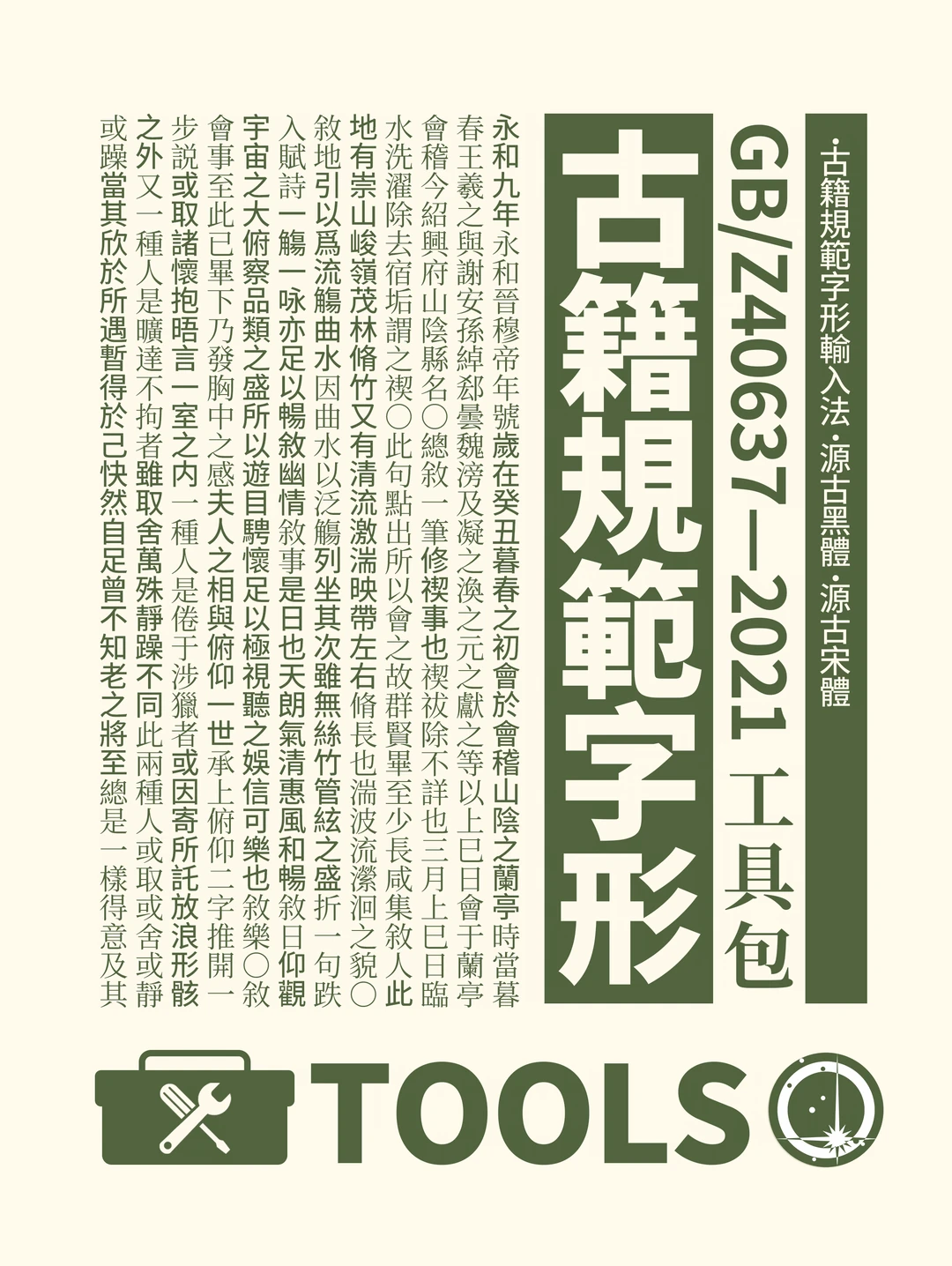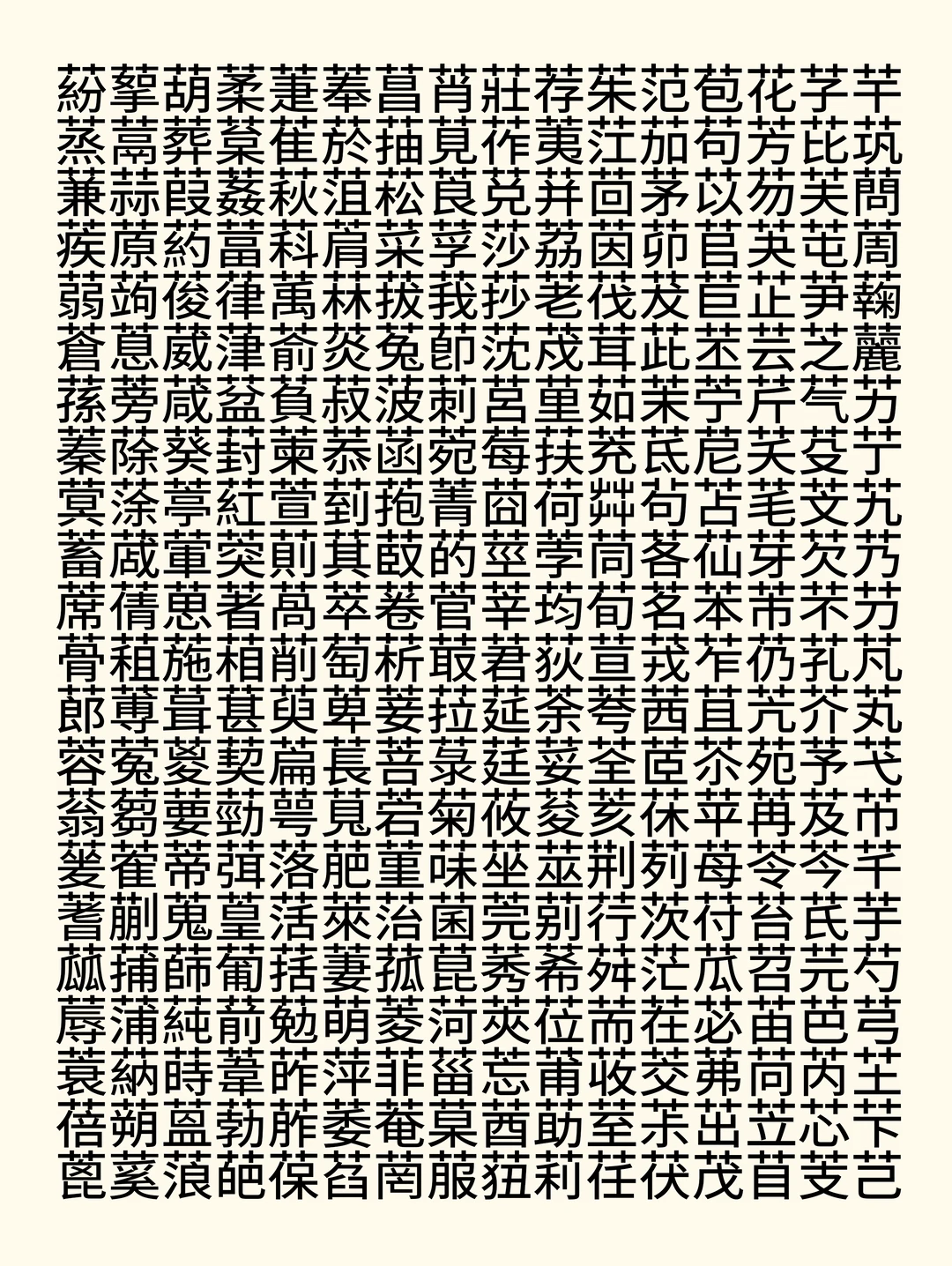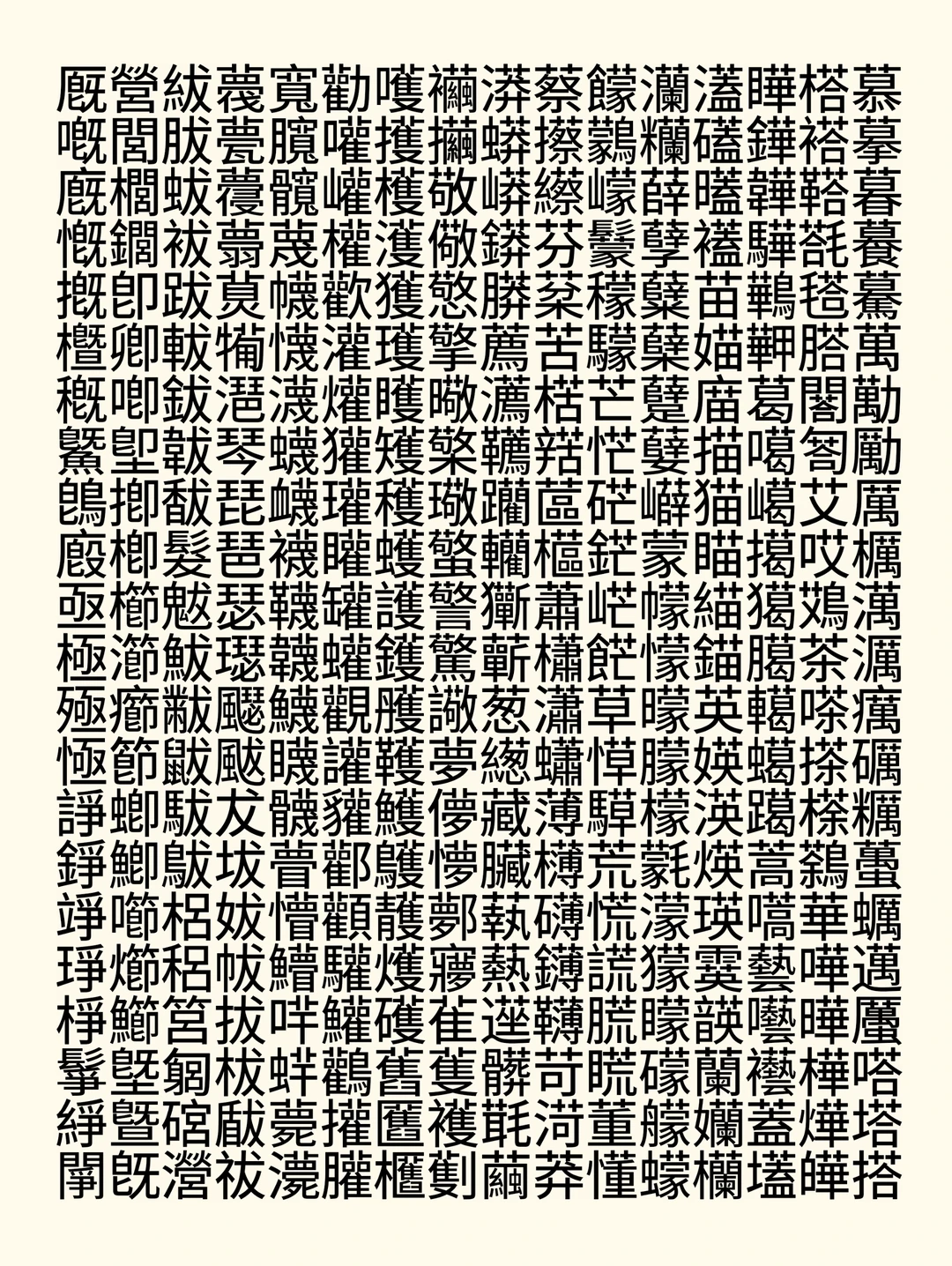
源古黑体是在思源黑体基础上调整的一款免费商用中文字体,字形专门参照《古籍印刷通用字规范字形表》(GB/Z 40637-2021)做了校对修改,整体遵循 SIL OFL 1.1 开源协议。设计时直接以思源黑体为基底,把里面各地不同的字形拆开重新搭配,再对照古籍表的规则挑选部分部件做统一处理,最终敲定了一版“真·国标繁体”的写法。碰到 Unicode 扩展 B 区那些极少用的字,则是从遍黑体里调来补充的,这样生僻字的覆盖面就更广了。这套字正好补上了古籍表推出后配套字库没跟上的空缺,核心是给古籍数字化和传统文化排版准备的。外观上它顺着思源黑体的脉络,维持着结构端正、气质中性、重心稳妥的现代黑体框架,线条清爽匀称,转折地方也收得利落。跟日常见到的标准黑体不同,它在其中揉进了早年复古照排黑体那种本土的温和气息,在屏幕上显示依然清晰利落,却没丢掉传统印刷字体的那份底蕴,观感上不那么冷硬。许可条款依旧走 SIL OFL 1.1 的路子,个人与企业都能免费拿来商用,支持嵌入软件、二次修改和自由传播,但做出的衍生版本必须继续套用这套协议,原始的字体文件本身是禁止单独出售的。实际使用里像古籍校注、传统文化类出版物、历史档案电子化、学术考据都挺适合用它,平时的长文阅读和版面编排也能顺手用上。
GB/Z40637-2021古籍规范字形工具包,展示源古黑体与源古宋体排版兰亭集序效果及TOOLS标志-刊刻Kntuk
密集排列的草字头汉字网格,包含芋、艽、芳、芎、芬等汉字-刊刻Kntuk
密集排列的汉字字符网格,展示大量不同字形的汉字-刊刻Kntuk
包含大量汉字及生僻字的字符矩阵-刊刻Kntuk
包含大量生僻汉字的字体排版展示图-刊刻Kntuk